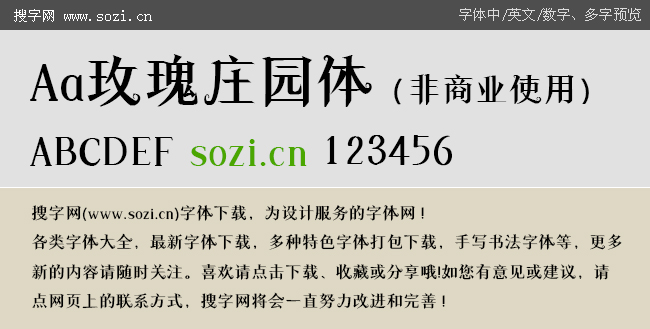
Aa玫瑰莊園體
搜字網(wǎng)給大家提供一款A(yù)a玫瑰莊園體(非商業(yè)使用)中文字體下載,Aa玫瑰莊園體是一款藝術(shù)字體,該字體以宋體字為基礎(chǔ)字形,將個別筆劃的收尾部分進(jìn)行了藝術(shù)變化,使字體增加了趣味性。適合應(yīng)用于海報設(shè)計、包裝設(shè)計、網(wǎng)頁設(shè)計等應(yīng)用(此字體為個人非商用版,商用可以聯(lián)系QQ:1006760504)。